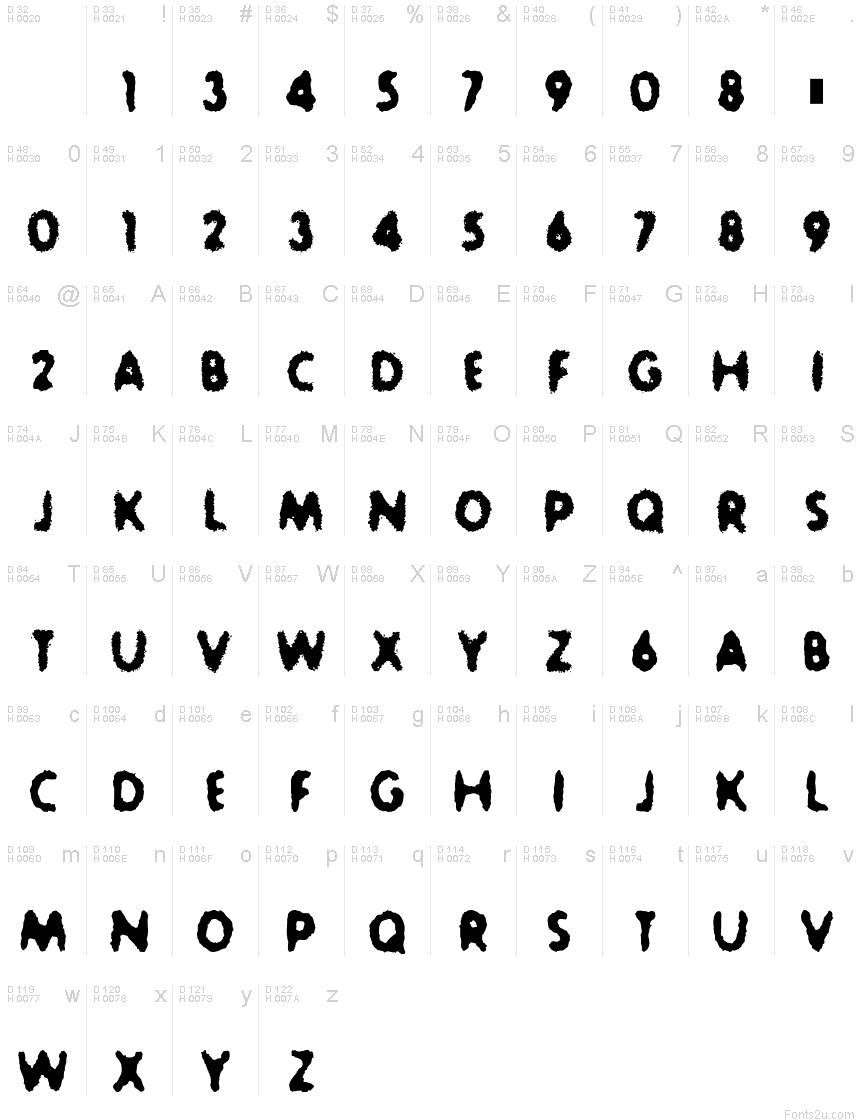
Sludge Bucket to darmowy, zniekształcony font typu display o błotnistym, ociekającym szlamem charakterze. Litery są grube, tępe i nierówne, z poszarpanymi krawędziami i grudkowatymi kształtami, które sprawiają wrażenie, jakby zostały wylane, a nie narysowane, co nadaje całości chaotyczny klimat horroru komiksowego.
Idealnie pasuje do plakatów, okładek zinów, grafik zespołów, ulotek na Halloween, tytułów gier i krótkich haseł na gadżetach, gdzie napisy mają wyglądać na brudne i niestabilne. Jako darmowy font najlepiej sprawdza się w krótkich nagłówkach, ponieważ spuchnięte, ociekające formy najlepiej prezentują się, gdy mają miejsce, by się rozlać i rozchwiać.
Sludge Bucket